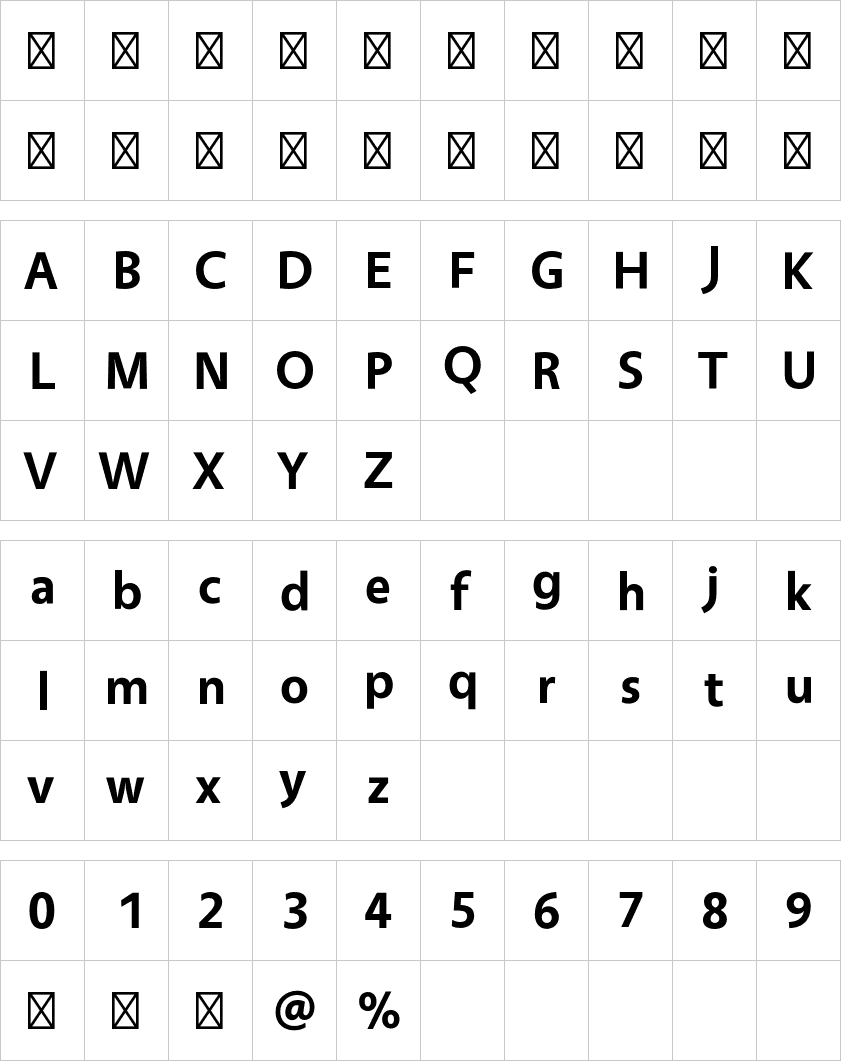
Vegur
Vegur 是一种人文主义无衬线字体,专为点冒号标识而开发。借着更新0.700版本的机会,我们重新审视了设计,修复了拉伸的部分,以创造出更锐利的印象。它还被调整为比之前的版本更长,整体看起来更干净。特别是,我认为已经推迟的粗体字号的印象通过这次更新有了很大的改变。
此外,我们还添加了大量字符,例如变音符号(添加到字母表中的符号)、连字(例如法语中的 Æ 和 Œ 以及德语中的 ß)。此外,我们还添加了英镑(英镑)和欧元(欧元)等代表性货币符号,以及欧洲国家的标点符号。尽管并非所有字符和符号均可用,但我们计划在未来的更新中添加更多字符和符号。